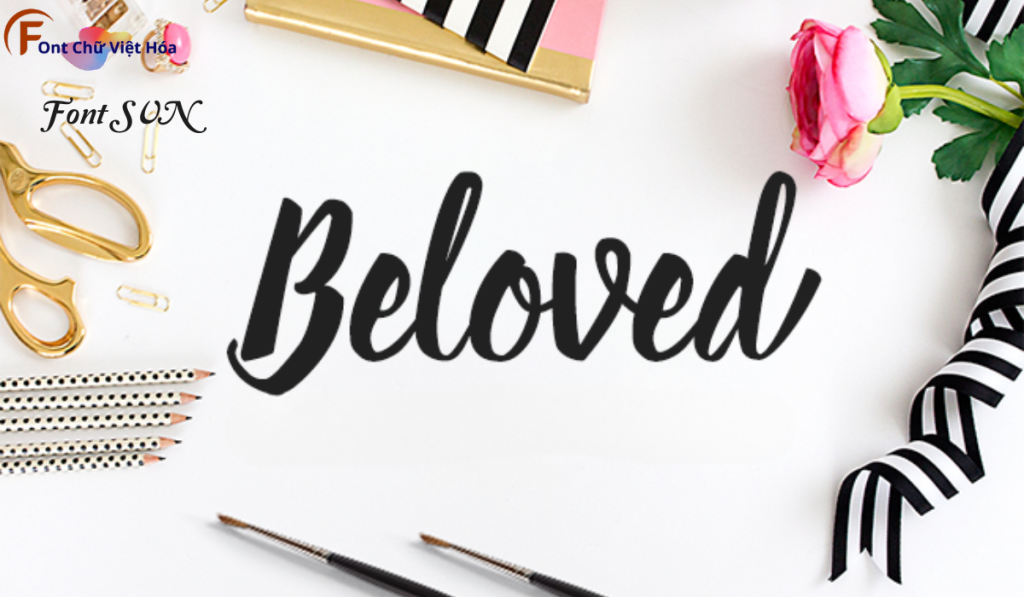
Font SVN Beloved Việt Hóa
Phân loại: Cá tính, Sáng tạo
Độ dày: Mỏng, Thường, Đậm
Font SVN Beloved Việt Hóa là một font chữ không chân hiện đại, thuộc bộ font SVN. Được thiết kế với mục tiêu mang lại sự tinh tế và thanh lịch, font này phù hợp cho các dự án thiết kế như website, tài liệu, và bao bì sản phẩm. Với các nét chữ rõ ràng và độ dày đều đặn, Font SVN Beloved Việt Hóa không chỉ dễ đọc mà còn tạo cảm giác chuyên nghiệp. Việc Việt hóa font giúp người dùng dễ dàng sử dụng trong các thiết kế tiếng Việt, mang lại sự tiện lợi và thẩm mỹ cao.